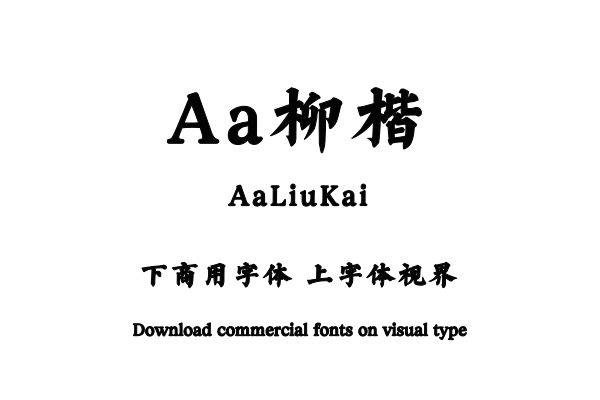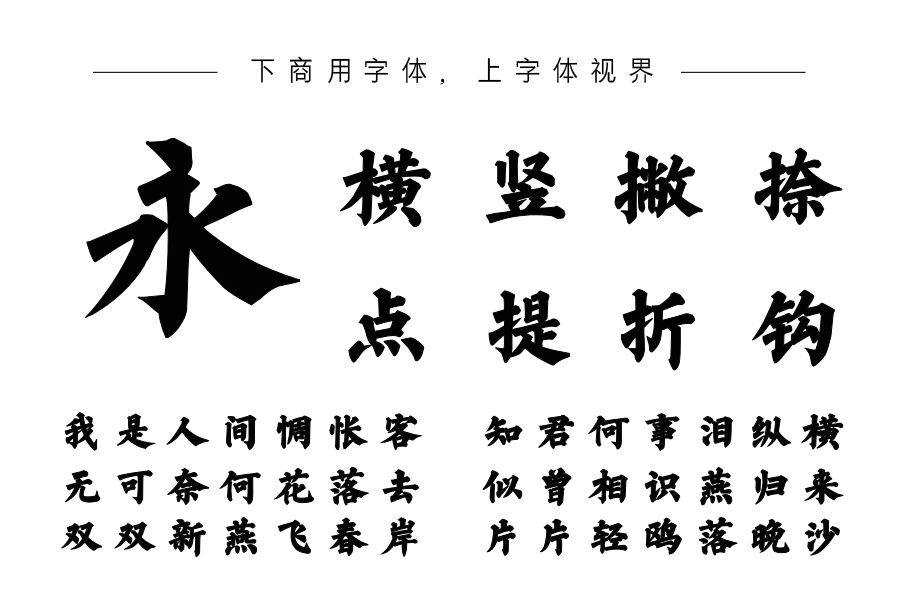
本字体以柳公权经典碑帖为基底,通过数字方式重绘字形,轮廓更加简洁现代,提取柳楷结构,结合现代字体构造逻辑,使最终产品字形更加均衡稳定而不失柳楷风骨。购买须知:“下载服务费”与“字体VIP”所获得字体 仅用于个人非商用, 商用请联系付费授权。本字体为电脑用字,手机没有root权限不支持直接手机换字(手机如何root,请自行百度搜索教程)。购买前请先 了解清楚后再付款 ,字体为虚拟产品无法回收 一旦购买不支持退款。